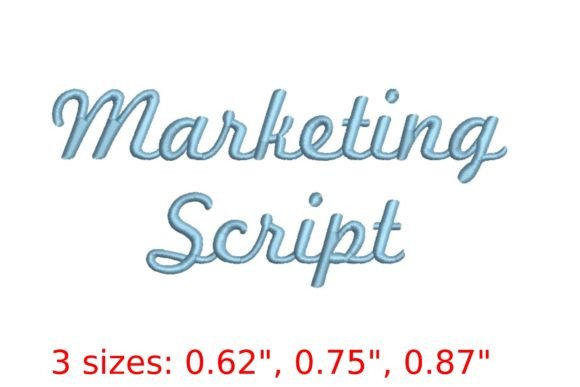
Marketing Script Embroidery Font
Việc tìm kiếm các thành phần thiết kế phù hợp có thể là một thách thức, nhưng Marketing Script Embroidery Font cung cấp một bộ sưu tập đặc biệt giúp nâng tầm công việc của bạn ngay lập tức.
Được chế tác với độ chính xác cao, Marketing Script Embroidery Font cung cấp các vector sạch, kiểu chữ mượt mà và giấy phép thương mại để bạn yên tâm.
Hoàn hảo cho thợ thủ công, nhà thiết kế đồ họa và chủ doanh nghiệp nhỏ muốn thêm nét chuyên nghiệp vào hàng hóa của họ.